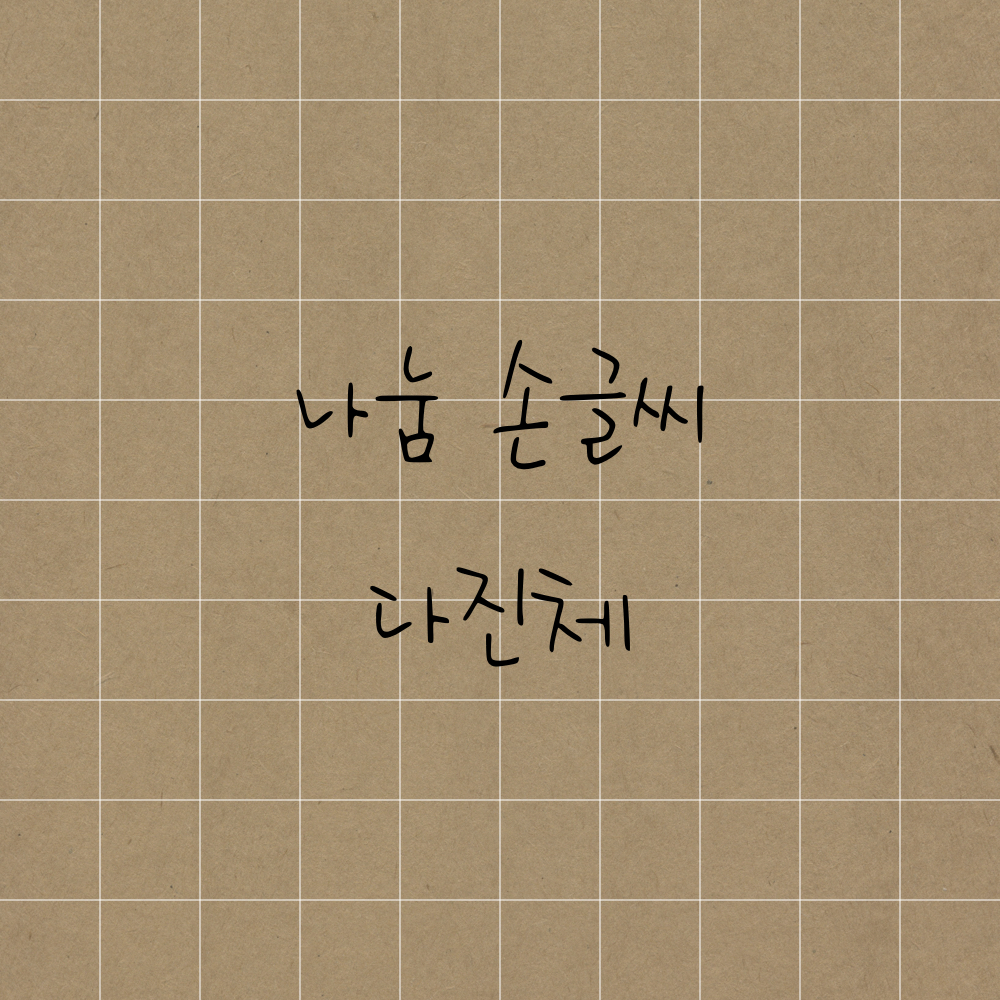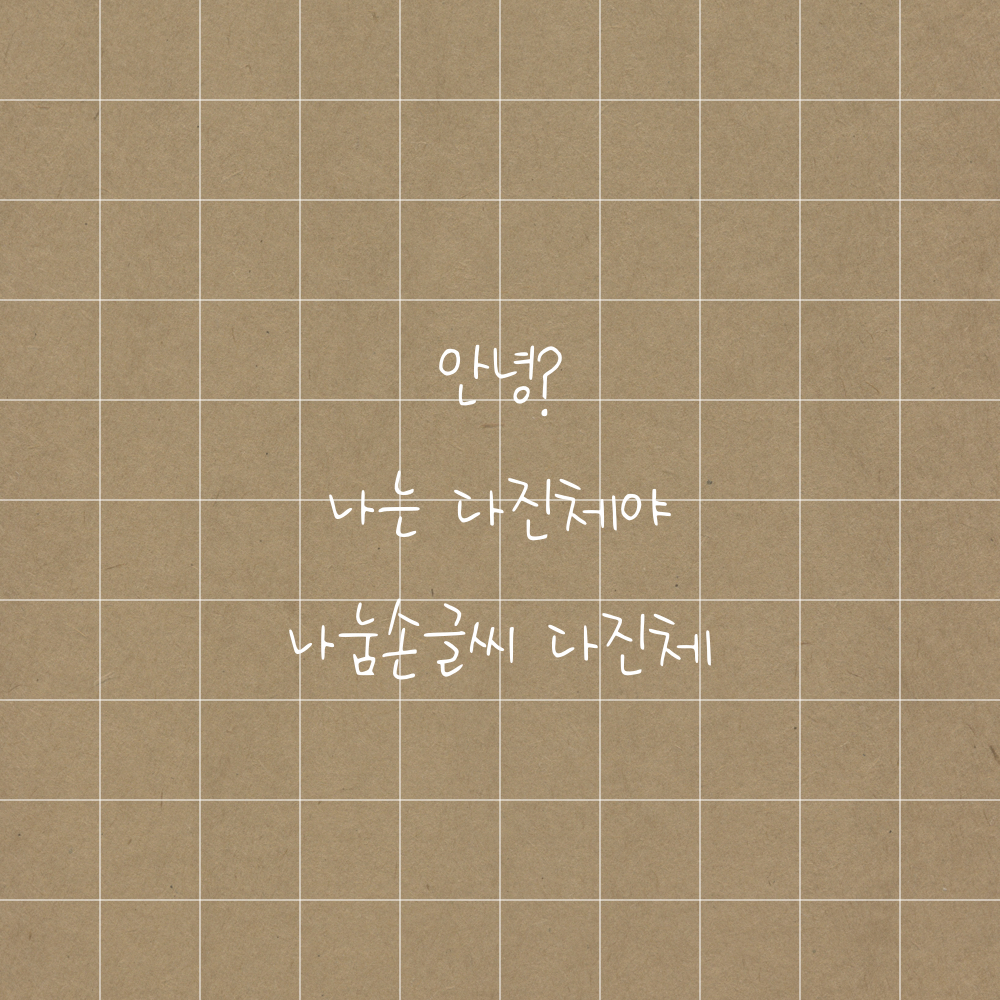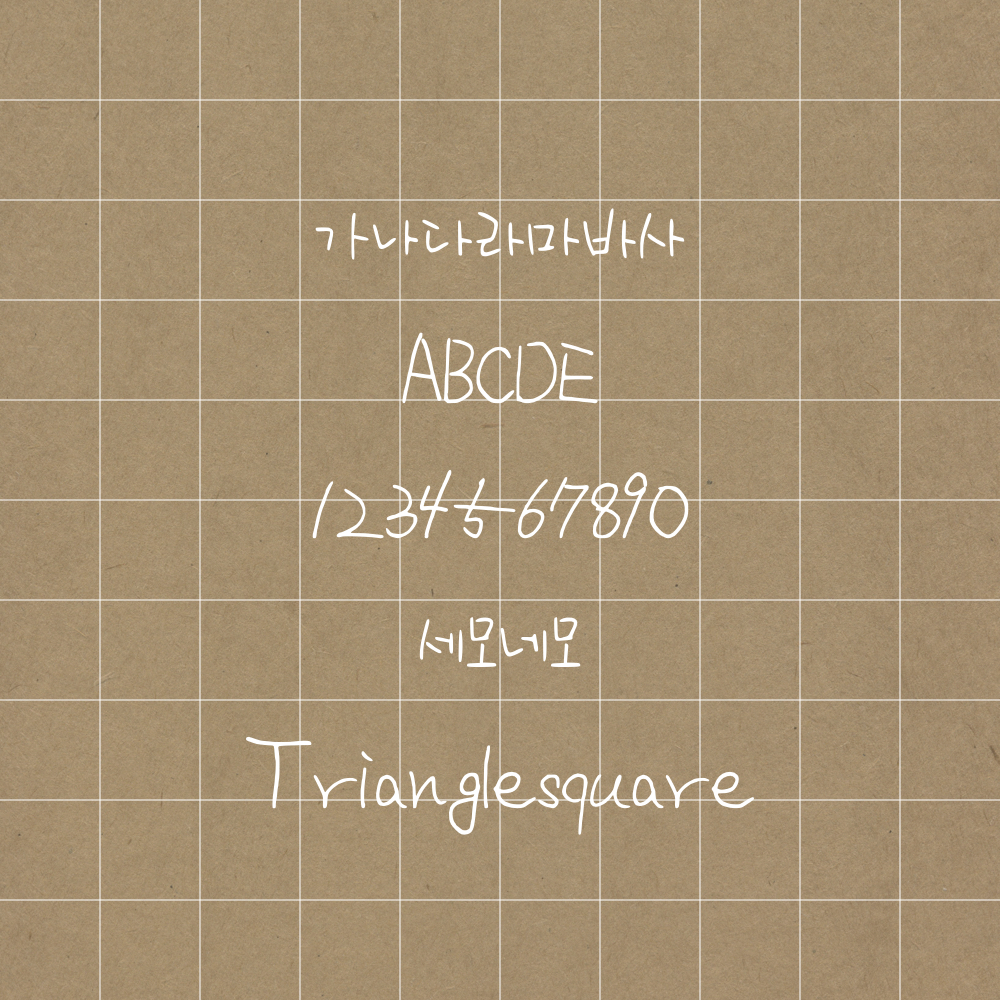
오늘의 폰트는 다진체입니다💛 벌써 30개가 넘는 폰트를 알아보았습니다. 마음에 드는 스타일을 발견하셨나요~?
오늘은 얇은 글씨 러버라면 다운로드 하지 않을 수 없는 폰틀를 준비했습니다. 한 번 알아볼까요~?
개인적으로 매우 제 스타일입니다.😆
저는 얇은 펜으로 쓰면 꼭 삐뚤삐뚤 악필처럼 보이는데요.
이 때문인지 얇은 두께의 폰트에 손이 자주 가더라고요😉
다진체는 두고두고 플래너에 사용할 것 같아 기대되는 마음입니다🤗
여러분도 얇은 필기체로 플래너를 꾸며보는건 어떨까요~?